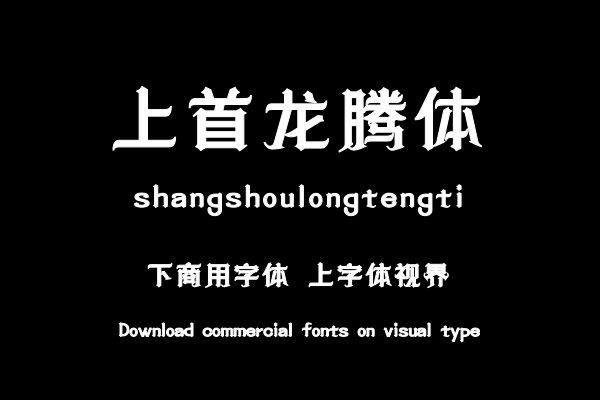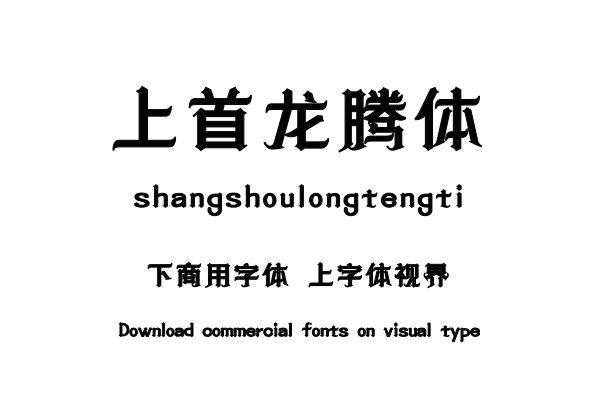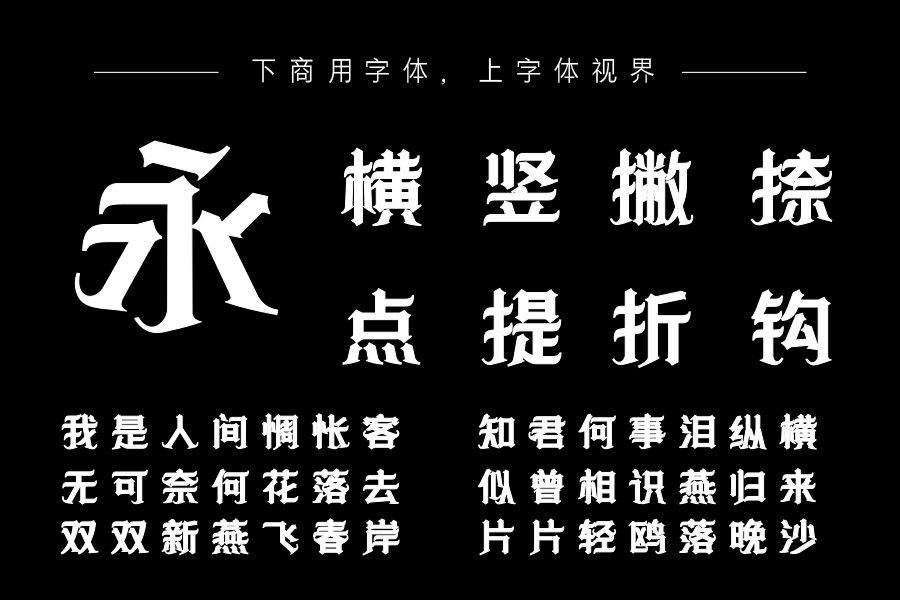
上首龙腾体,整体字型笔画尖锐、简约、随性而有个性,整体给人一种干净简洁的感觉,对字体的笔画做出修饰的变化,犹如图腾笔划与笔划相互交错。适用于搭配标志、广告标语、......购买须知:“下载服务费”与“字体VIP”所获得字体 仅用于个人非商用, 商用请联系付费授权。本字体为电脑用字,手机没有root权限不支持直接手机换字(手机如何root,请自行百度搜索教程)。购买前请先 了解清楚后再付款 ,字体为虚拟产品无法回收 一旦购买不支持退款。